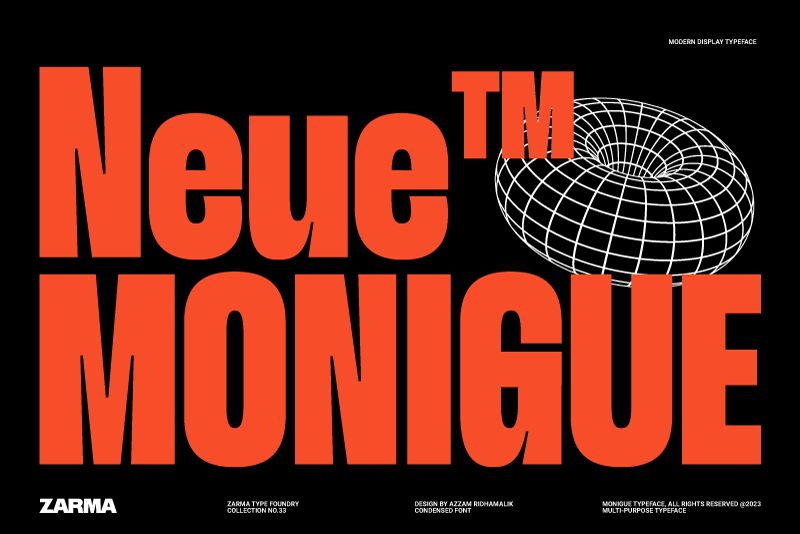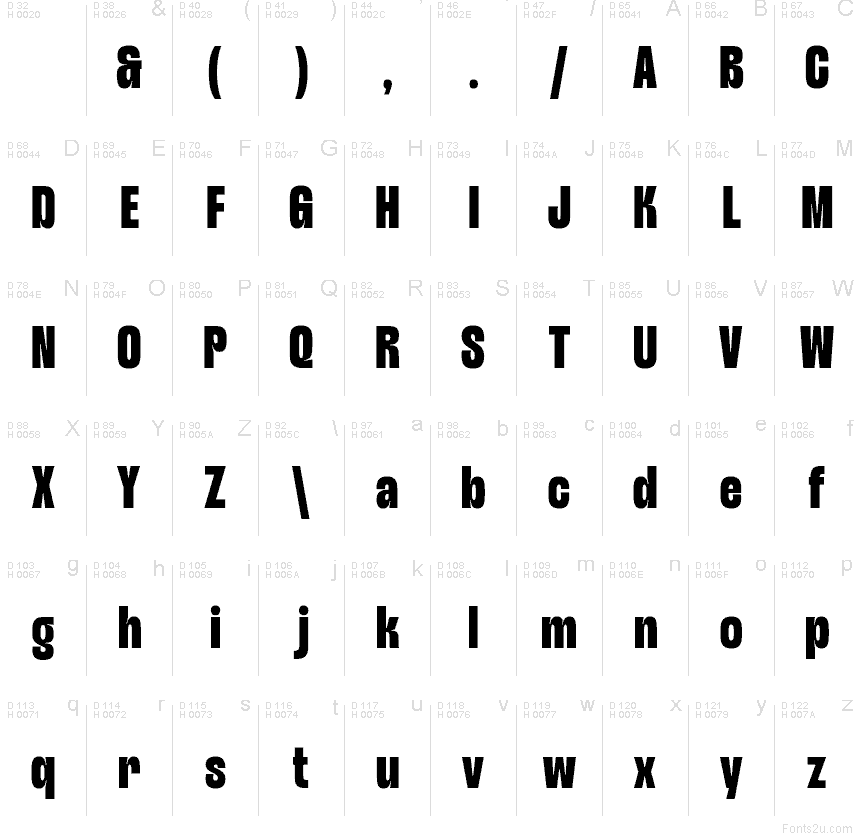
Monigue, font creata da Azzam Ridhamalik di Zarma Type Foundry, è un carattere sans serif condensato gratuito, caratterizzato da un'impronta forte e decisa, ammorbidita da curve sorprendentemente fluide. Le sue proporzioni slanciate e la spaziatura ridotta creano blocchi di testo solidi, mentre i bordi arrotondati evitano che il peso visivo risulti troppo aggressivo. Il risultato è un font sicuro e d'impatto, che cattura l'attenzione fin dal primo sguardo.
Utilizzare Monigue su poster, grafiche streetwear, copertine di album, miniature YouTube, volantini per eventi, branding sportivo e titoli web audaci conferisce immediatamente grande carattere ai tuoi design. Questo font gratuito è ideale anche per brevi richiami su packaging dove lo spazio è limitato. Abbinalo a una grotesk leggera e pulita o a una serif semplice, e aumenta leggermente il tracking se il testo ti sembra troppo denso.